Langdon
Giới thiệu với các bạn Langdon, một mẫu chữ ra đời nhờ sự hợp tác của XLN Telecom và chuyên gia thiết kế hàng đầu Steven Bonner. Mẫu chữ đậm đà và khỏe khoắn này sẽ khiến thiet ke web của bạn hút được ánh nhìn của người xem ngay từ đầu.
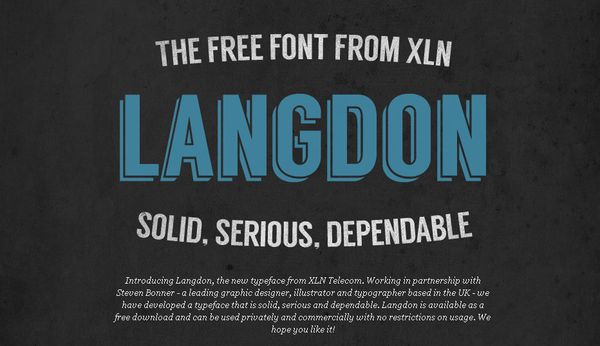
Canter free font
Canter là một mẫu chữ được thể hiện với 6 kích cỡ khác nhau. Nó được dùng để viết tiêu đề, headline và poster.
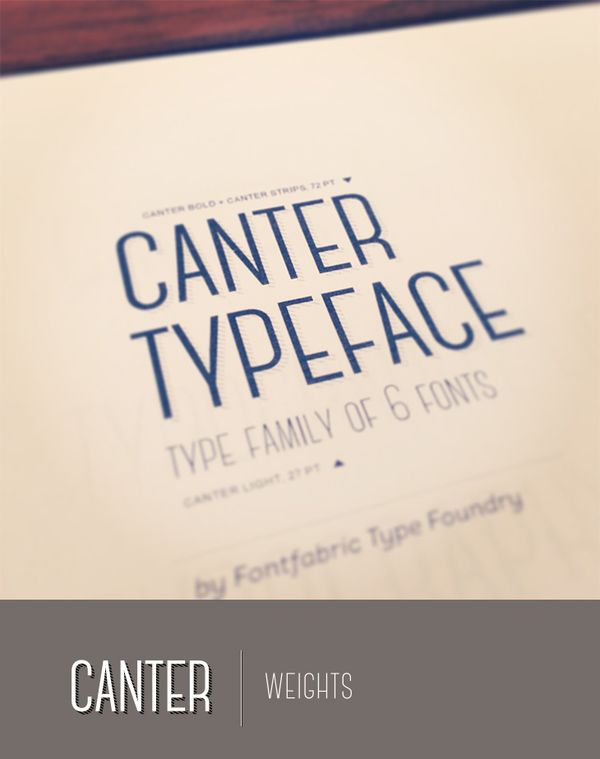
Braxton free font
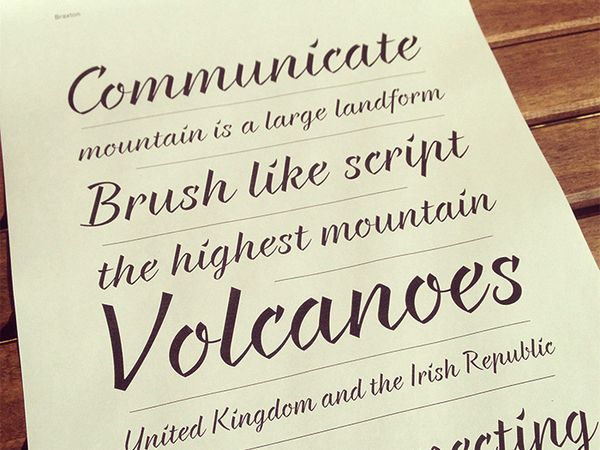
Akura Popo Free Font
Akura Popo mà phong cách vintage và cổ điển, sử dụng serif font đậm đà, khỏe khoắn. Nó phù hợp đặt trong các logo, headline, leatterhead, các web chủ đề thể thao…Nó có sẵn ở dạng OTF và cả TTF.
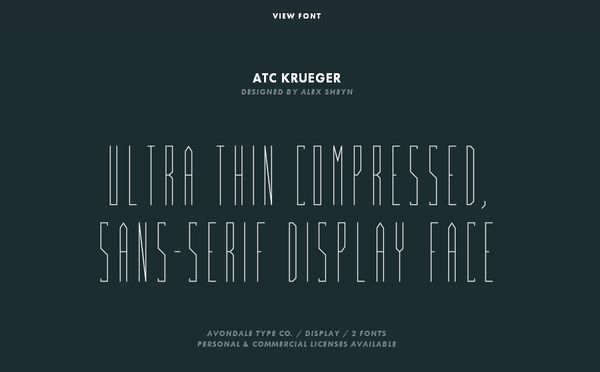
ATC KRUEGER
ATC KRUEGER bao gồm 100+ ký tự với đầy đủ bảng chữ cái và số.
Boomtown Deco
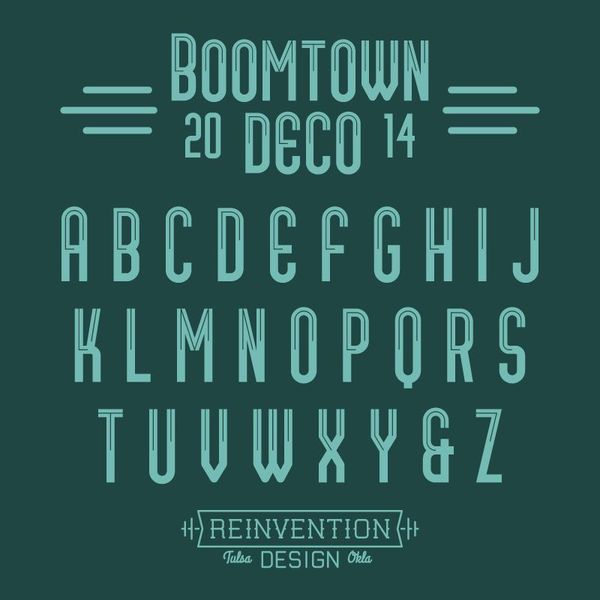
Calendas Plus
Caledas Plus được cải biên từ những mẫu chữ cổ xưa.
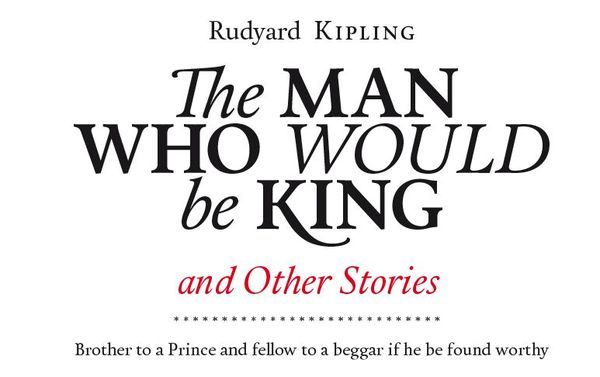
Cinzel
Cinzel có mặt chữ được lấy cảm hứng từ kiểu chữ Roman thế kỷ thứ nhất.